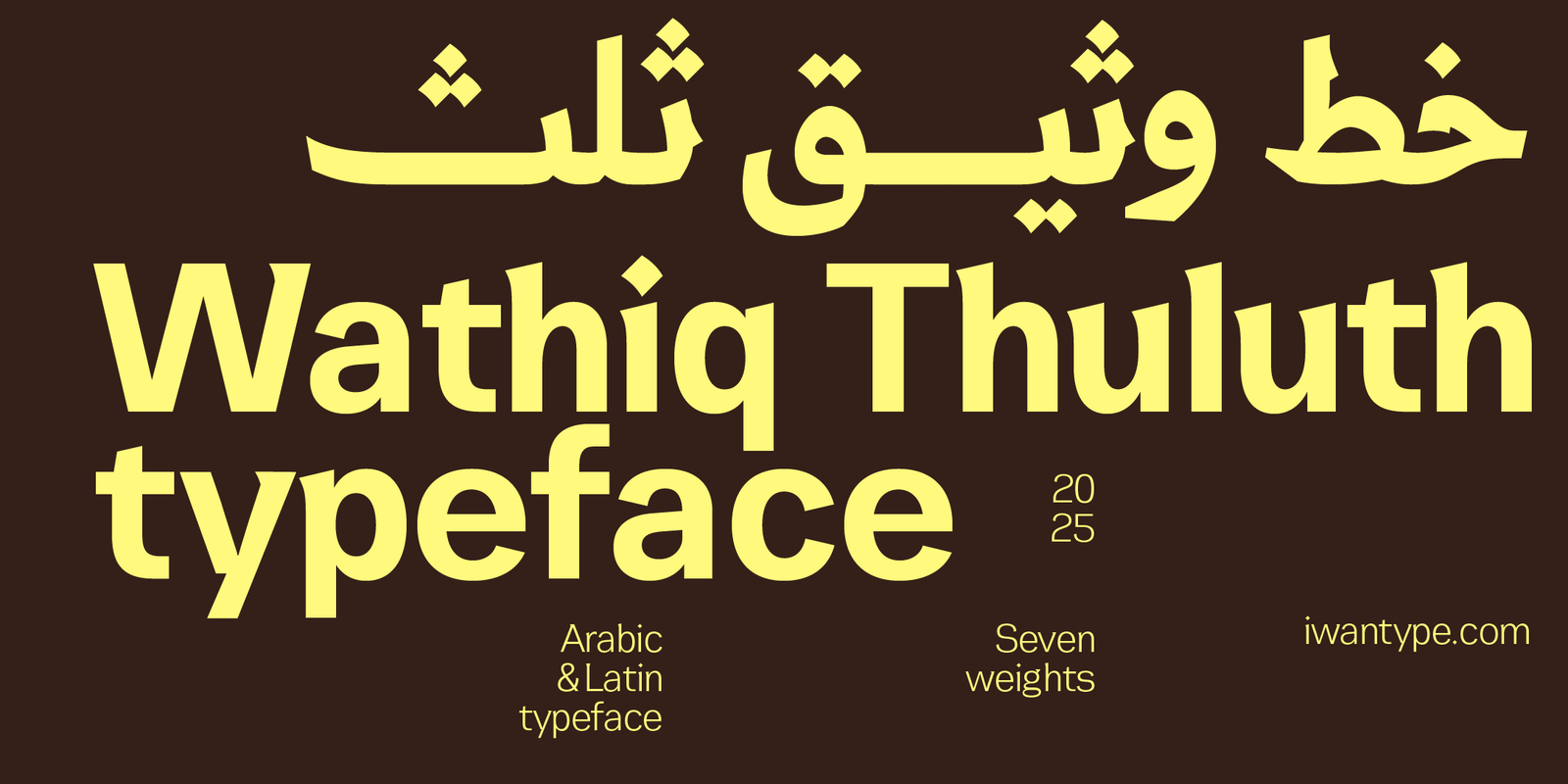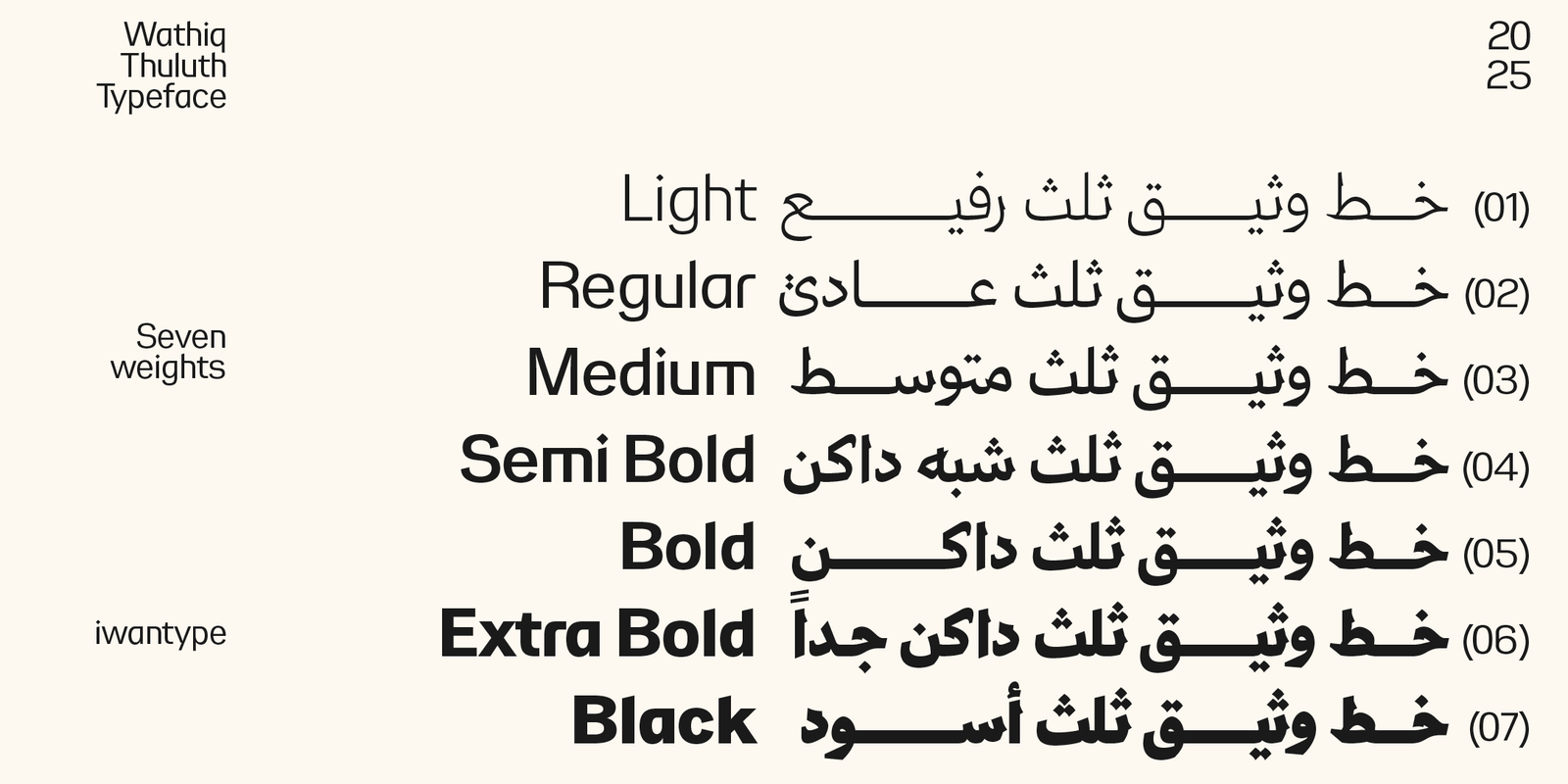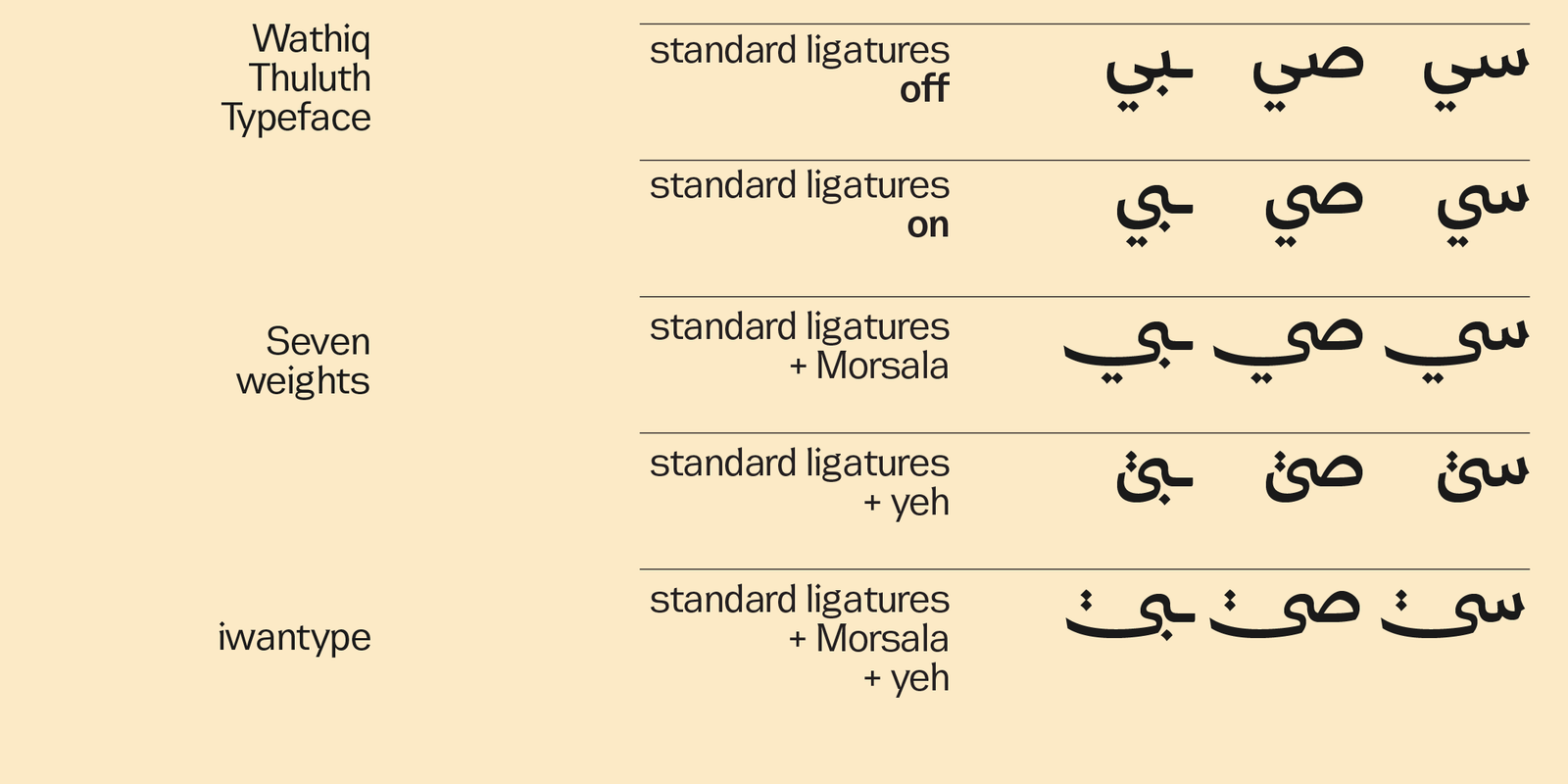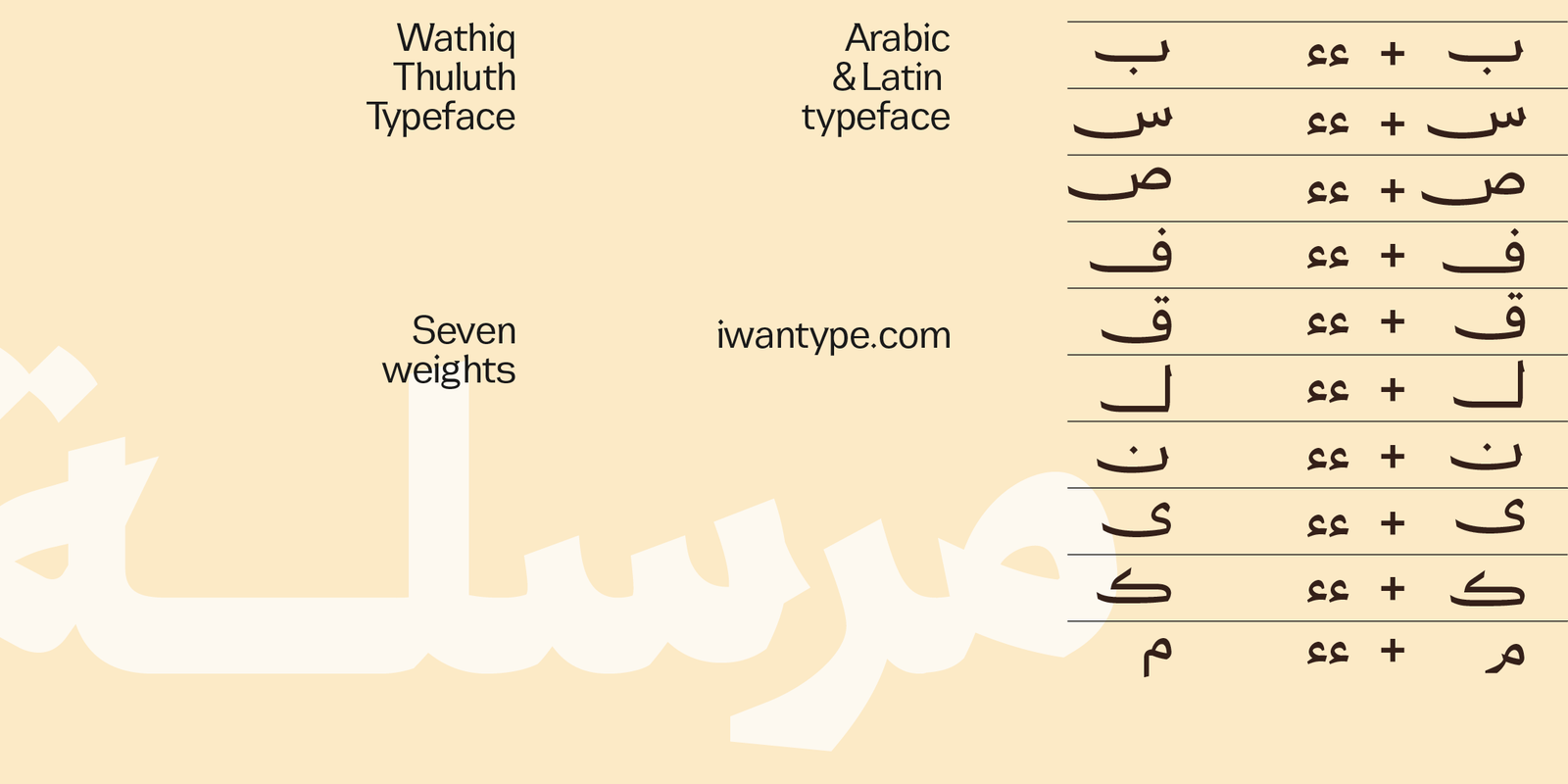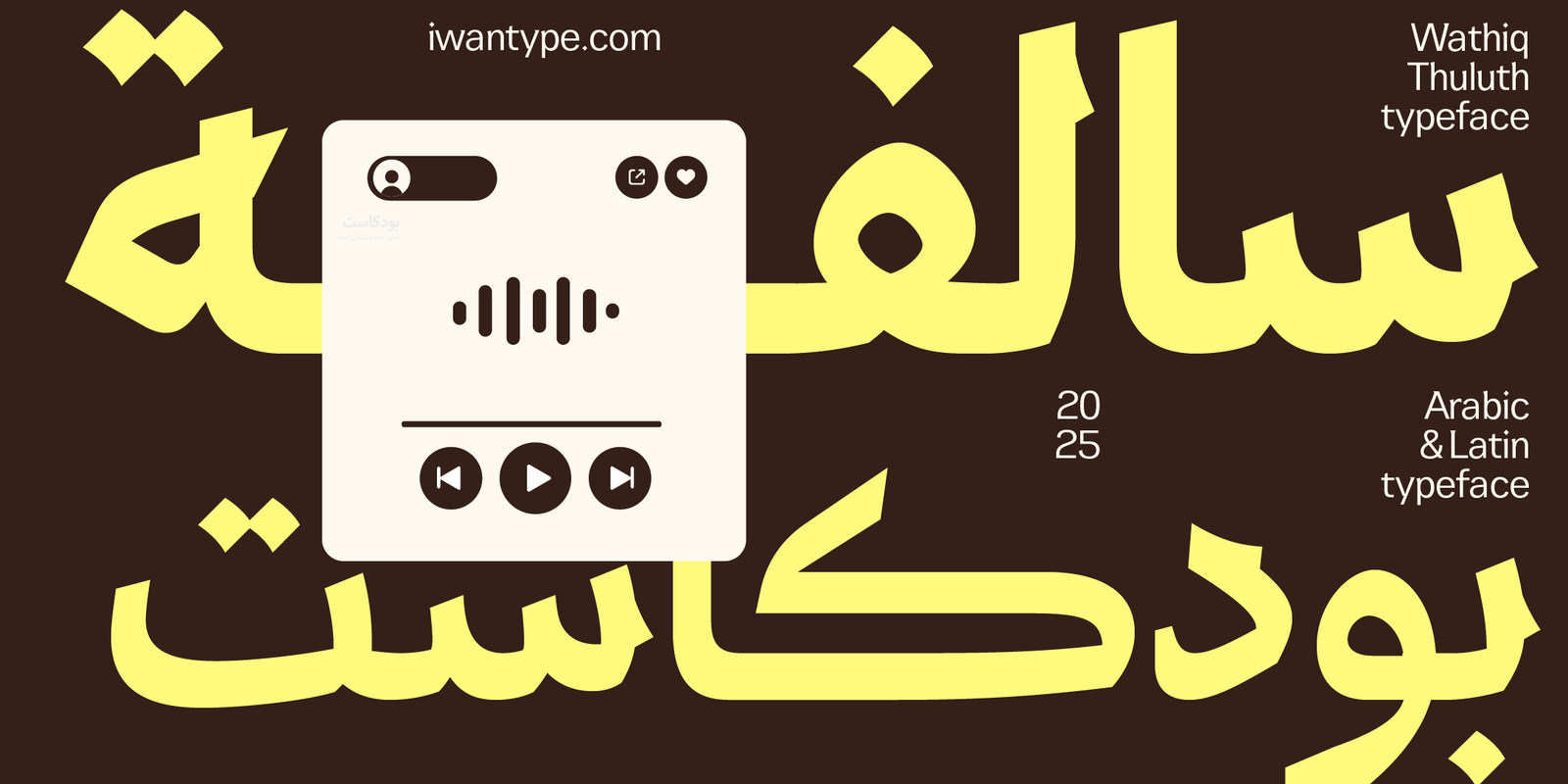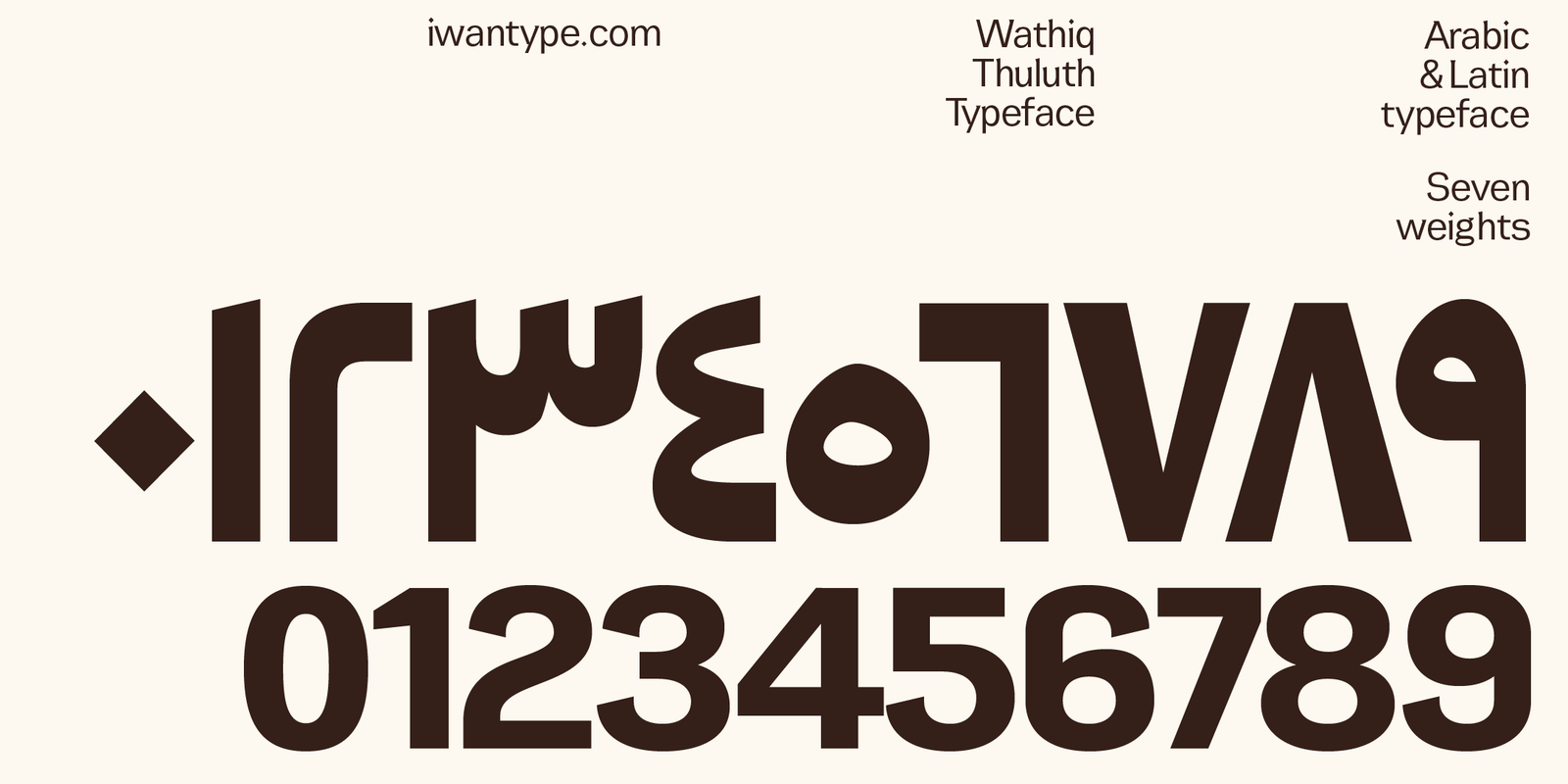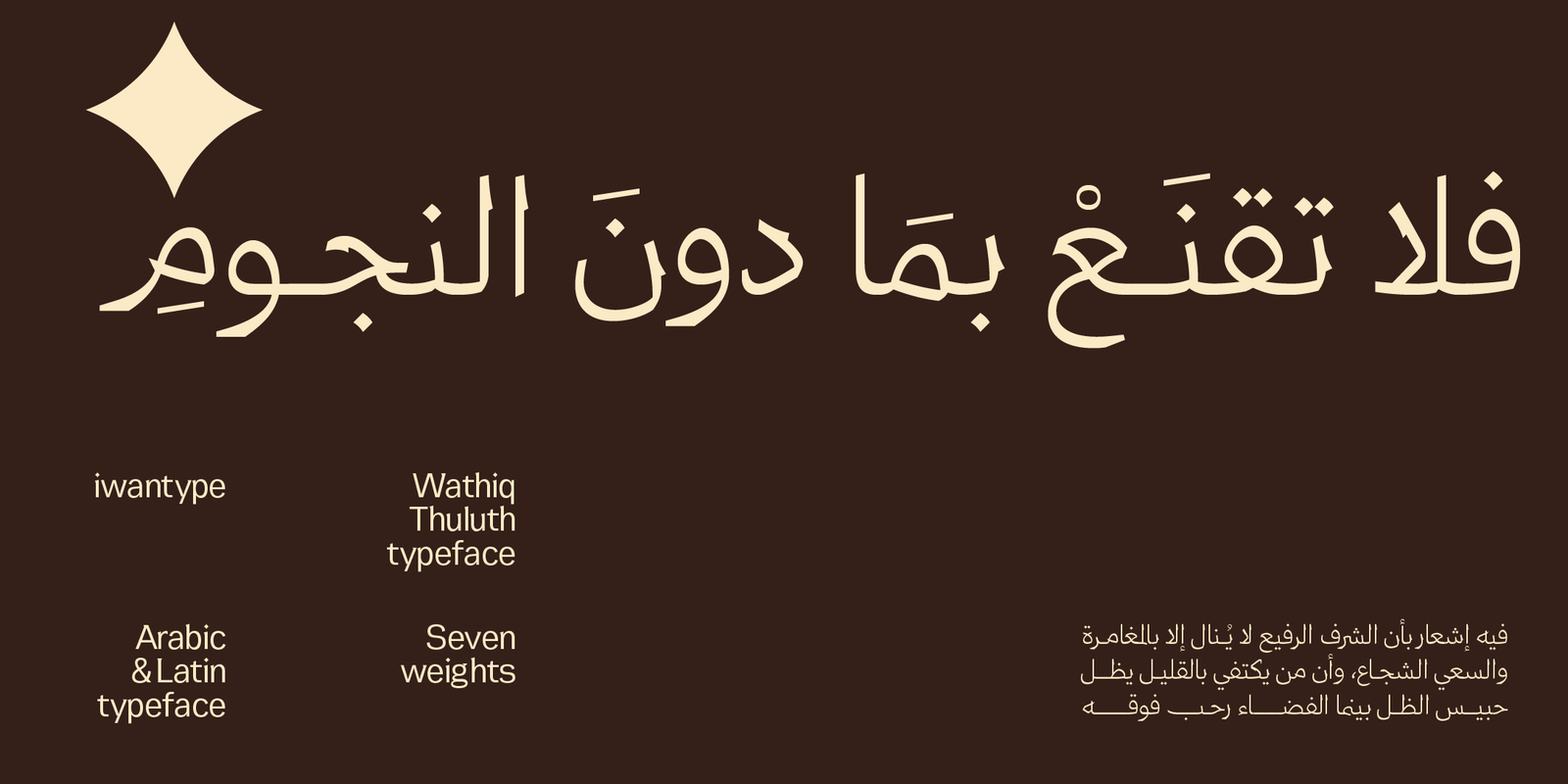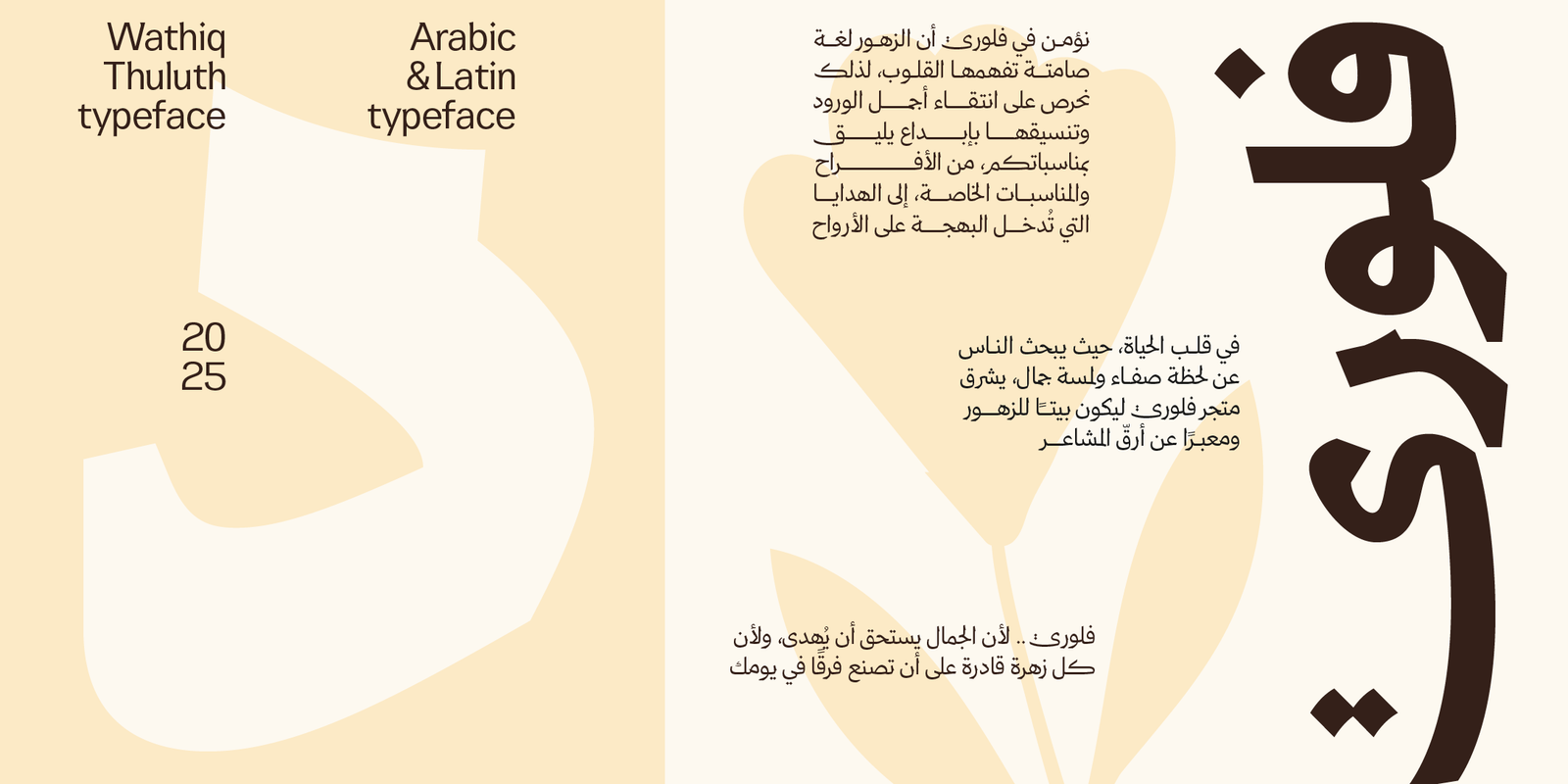
خط وثيق ثلث – Wathiq Thuluth Typeface
وثيق ثلث – Wathiq Thuluth Typeface
هو الإصدار الجديد من عائلة خط وثيق، يجمع بين روح النسخ في وضوحه وانسيابيته، وفخامة خط الثلث في تكويناته وامتداداته الراقية.
تم تصميمه بروح معاصرة تحافظ على التوازن بين الأصالة والحداثة، مما يجعله مثاليًا للهوية المؤسسية، العناوين، الإعلانات، والمشاريع التي تبحث عن حضور بصري قوي.
مميزات خط وثيق:
يتضمن الخط العديد من مزايا OpenType التي تضفي عليه مرونة وتنوعًا في الاستخدام، مثل:
- أحرف مرسلة (تُفعَّل بإضافة “ءء” بعد الحرف)
- حرف ياء بنزول أقل: يقلل من نزول السطر، مما يعزز من انتظام النصوص.
- أحرف المركبة: تسهم في تحسين المظهر العام للنص وتزيد من سلاسته.
- نقاط بديلة
- يدعم رمز الريال السعودي، ويمكن تفعيله بإضافة حرف “ء” بعد كتابة كلمة “ريال”.